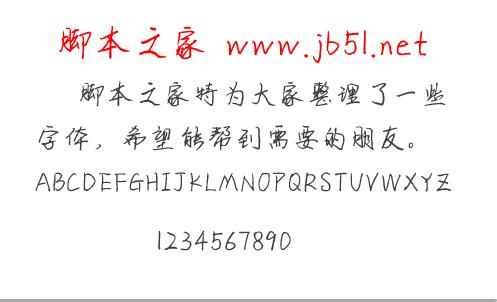
忆情永不忘是一款十分好用,且非常漂亮的中文字体,同时也是由文道字库倾情发布的作品,字体犹如疾风般的行云,展现出了侠客般的豪情万丈,极为舒适,适应于报纸和杂志和书籍中常用字体海报、个性促进品牌标志设计、文本装潢、信息展示、篆刻制模英文、数据制作、装潢设计、视觉设计、字帖等一切合法应用场景,有喜欢的朋友可免费下载收藏。